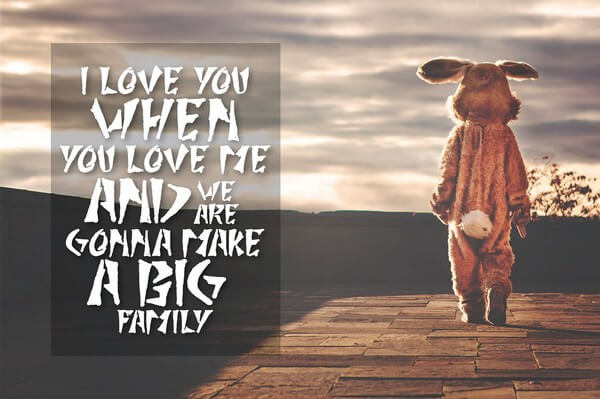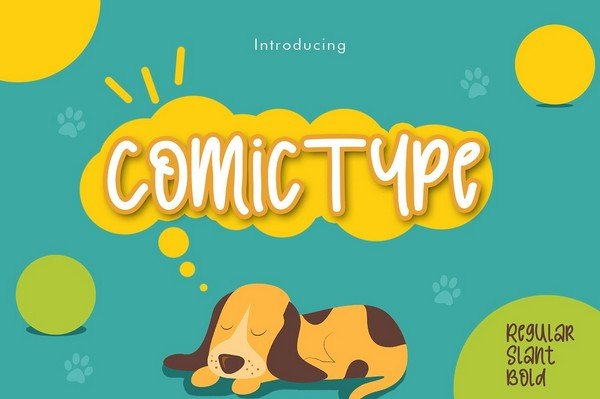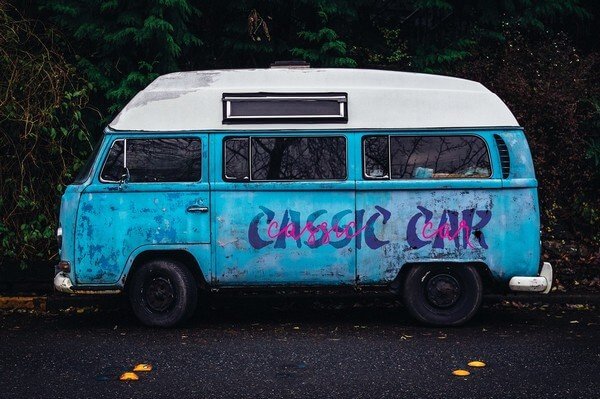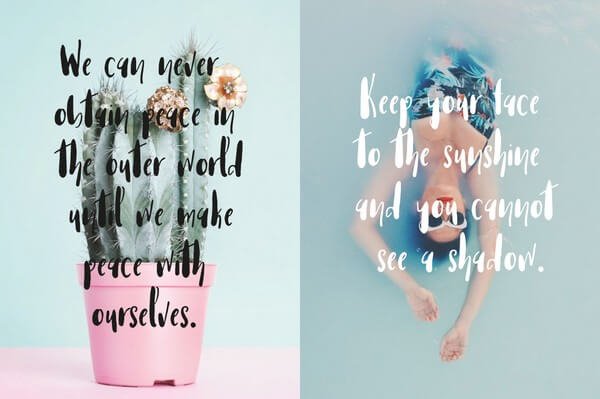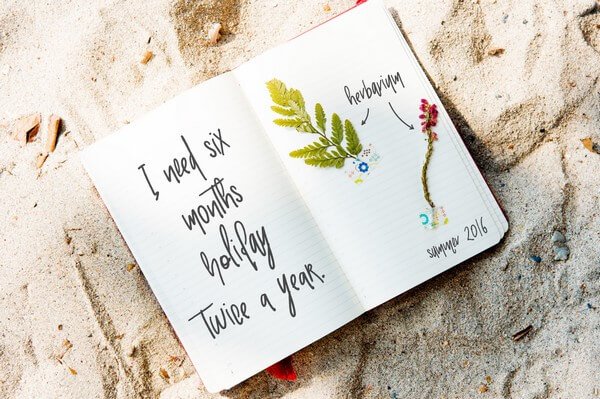
Lascia che i tuoi disegni si distinguano con questo pacchetto di caratteri hipster
Pubblicato: 2018-01-03La creazione di design unici, che si tratti di un sito Web, loghi, volantini, merchandising, materiale di marketing, ecc. è l'obiettivo di ogni designer. Più unico è il tuo lavoro, più ti distingui come designer e più clienti avrai.
Il tipo di font che usi per i tuoi progetti è una parte enorme del tuo lavoro. I caratteri distingueranno i tuoi progetti dagli altri. Ecco perché è importante che tu scelga solo il miglior font disponibile quando crei i tuoi progetti e le agenzie di branding professionali lo gestiscono molto bene.
Il lavoro di progettazione è notevolmente avanzato, rendendo più facile per i creativi trovare numerose risorse per rendere eccezionale il loro lavoro finito.
Oggi ti presentiamo il pacchetto di caratteri Hipster. Questa è una vasta collezione di caratteri di alta qualità con una varietà di caratteri, floreali, scritti a mano, display, formali, frivoli, divertenti e molti altri tipi di caratteri.
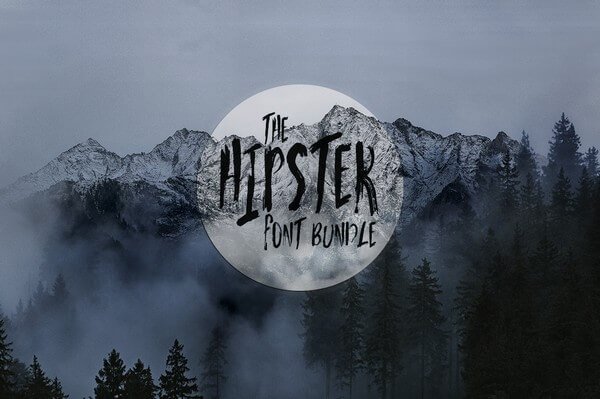
Il pacchetto accuratamente selezionato di 68 diversi tipi di caratteri renderà i tuoi progetti immediatamente hipsterifici e alla moda per soddisfare le esigenze attuali dei tuoi clienti.
Con una combinazione unica di caratteri, questo pacchetto ti consentirà di raggiungere qualsiasi tipo di cliente che hai e di lasciarli completamente impressionati! Il pacchetto ti consente di creare tonnellate di design diversi, tutti con i loro temi unici.
Il pacchetto di caratteri hipster renderà i tuoi progetti unici e si distinguerà dal tipo di designer di tutti i giorni. Puoi creare modelli hipster specifici, anticonformisti e totalmente accattivanti. Avrai progetti che le persone vorranno guardare in ogni momento.
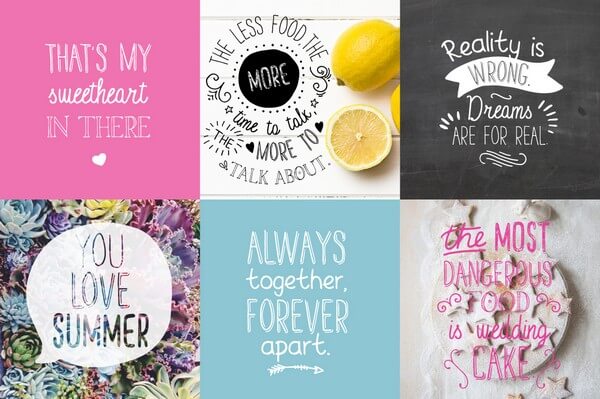
Dove puoi usare i caratteri Hipster per migliorare i tuoi progetti?
Ci sono tanti modi in cui puoi usare i caratteri hipster, tra cui:
- Etichette
- Loghi
- Vestiario
- Titoli di film
- Titoli dei volantini
- Concerti o copertine di album
- Testo comico
- Citazioni scritte a mano
- Confezione del prodotto
- Newsletter
- Poster
- Merce
- Progetti di branding
- Biglietto d'auguri
- Casi
Tra molti altri progetti.
Vantaggi dell'utilizzo dei caratteri Hipster
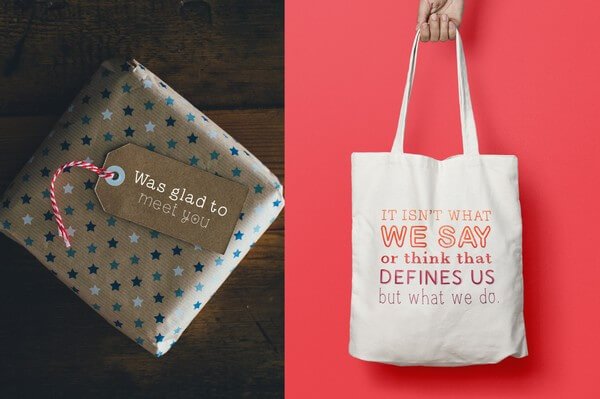
Comunicano il messaggio visivo del tuo sito
Quando un utente atterra sul tuo sito web semplicemente guardando i tuoi caratteri, può dire il tipo di atmosfera che stai cercando di comunicare. I tuoi caratteri diranno se vuoi essere visto come serio, divertente, casual, professionale, ecc.
Il tipo di layout che hai sul tuo sito web sarà completato dal tipo di caratteri che hai. I caratteri Hipster ti danno la possibilità di utilizzare caratteri che evocano il tipo di sentimenti ed emozioni che desideri che i tuoi visitatori provino quando atterrano sul tuo sito web.
Promuovono il tuo marchio
I caratteri svolgono un ruolo enorme quando si tratta di branding. Un logo aziendale definisce in gran parte il suo marchio. Con i caratteri hipster, puoi creare loghi unici che mettono in risalto il marchio del tuo cliente e lo mantengono in cima alla mente dei loro clienti poiché sarà memorabile. Se hai difficoltà a trovare il tono giusto per il tuo marchio, assumere un'agenzia di design del marchio è una buona idea per ottenere istruzioni dai professionisti e aumentare la tua credibilità.
Guidano i lettori attraverso i tuoi contenuti
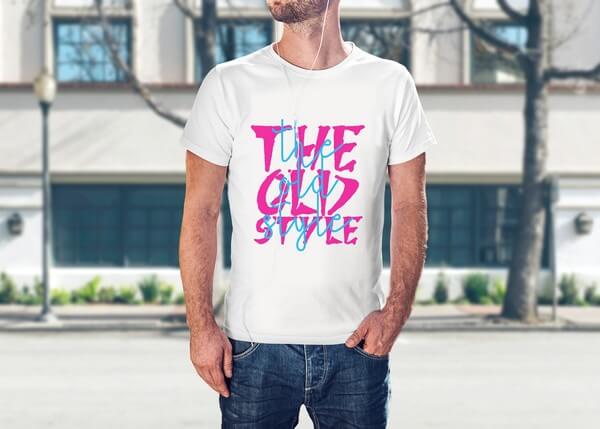
Leggere enormi blocchi di contenuti non è esattamente così divertente. I lettori vogliono leggere ciò che è più importante per loro. Non leggeranno quasi mai tutto ciò che hai scritto sul tuo progetto.
Che si tratti di contenuti sul tuo sito Web o contenuti promozionali di marketing su materiale promozionale come poster, pubblicità, ecc. Vogliono scansionare direttamente i dettagli importanti.
L'uso di una combinazione di caratteri hipster con stili, dimensioni e colori dei caratteri diversi sui tuoi progetti aiuterà a guidare i lettori attraverso i tuoi contenuti e indurli a leggere il più possibile. Usa caratteri diversi per evidenziare messaggi diversi sui tuoi progetti.
Rendono i tuoi contenuti attraenti
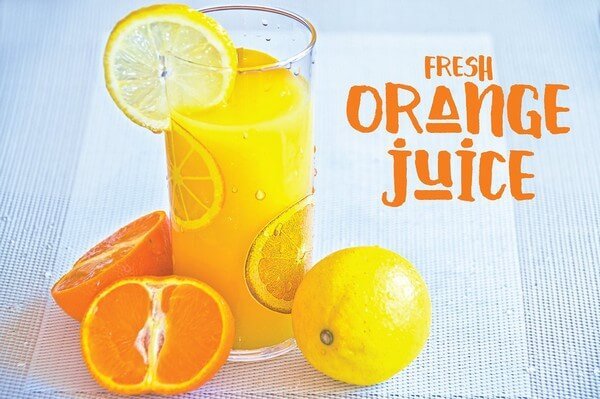
Le immagini sono più attraenti del testo. Laddove non hai il lusso di utilizzare elementi visivi come le immagini, sfrutta i caratteri hipster per rendere il tuo testo più attraente per i lettori.
La scelta del font giusto determinerà anche il successo dei tuoi progetti. Vuoi che i clienti siano in grado di vedere la tua creatività e questo puoi facilmente ottenere dando loro design che non sono solo unici ma alla moda e corrispondono alle tendenze moderne.